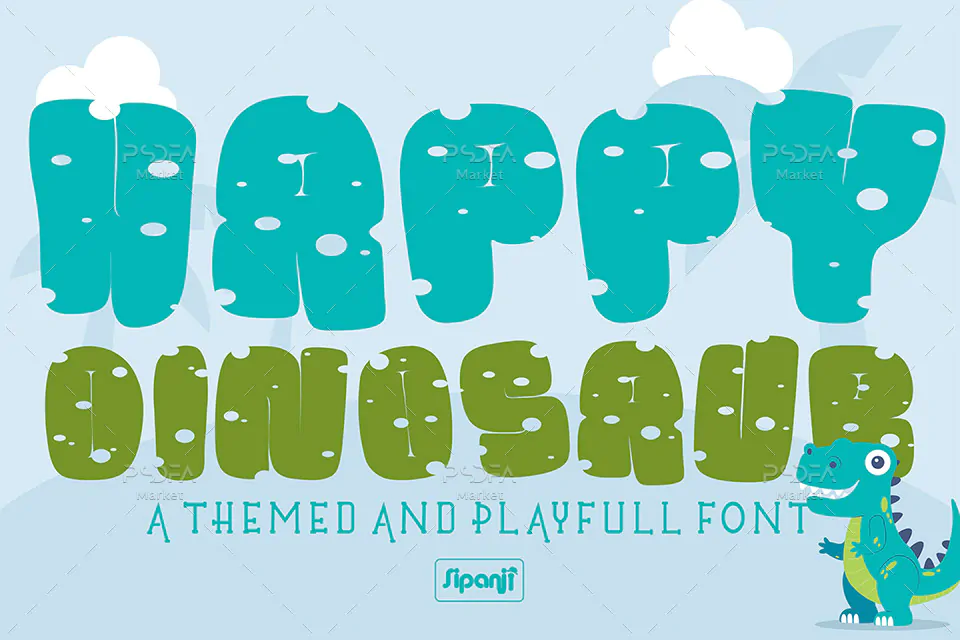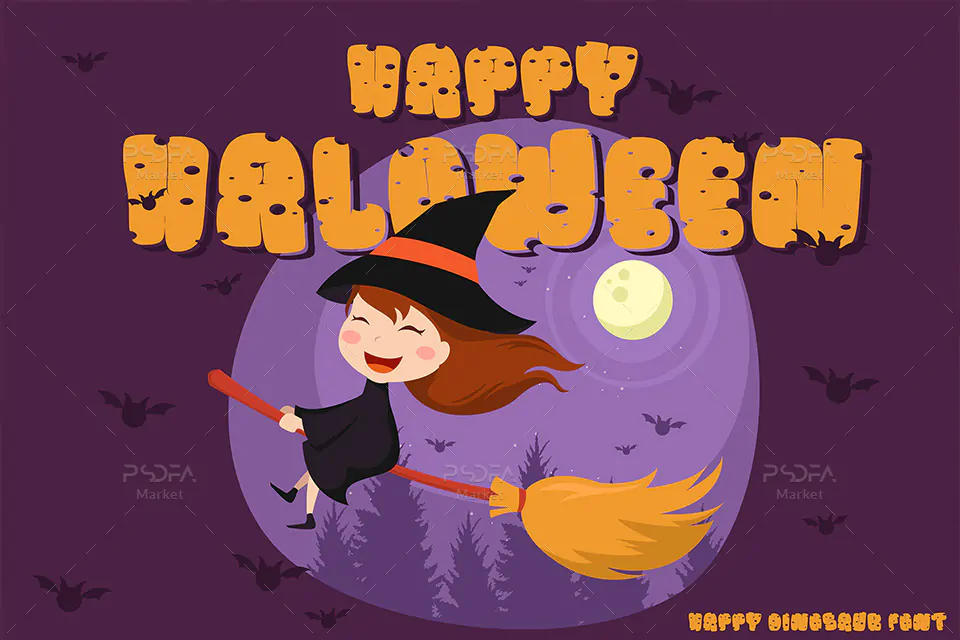
فونت کودکانه و کارتونی شاد و بامزه
فونت کودکانه و کارتونی شاد و بامزه دایناسور Happy Dinosaur یک قلم فوق العاده زیبای انگلیسی است که مناسب جهت استفاده در طرح و پروژههای گرافیکی مختلف به خصوص طراحی انواع تصاویر کودکانه و کارتونی میباشد. این فونت زیبا در قالب 2 فایل OTF, TTF در فایل محصول قرار دارد که با نصب یکی از این 2 فرمت در پوشه فونتهای سیستم میتوانید از این فونت انگلیسی در تمام نرم افزارهای گرافیکی و تایپ متون همچون فتوشاپ، افتر افکت، پریمیر، ورد، پاورپوینت و … استفاده کنید.
فونت شاد و بامزه Happy Dinosaur در وزن معمولی (Regular) طراحی شده است که میتوانید از آن در طراحی بسته بندی محصولات، لوازم التحریر، بگهای خرید و هدیه، ظروف یکبار مصرف، رابط گرافیکی گیم، تقویم، پوستر، بنر، بروشور، تراکت، چاپ تیشرت و دیگر طرحهای گرافیکی استفاده کنید.